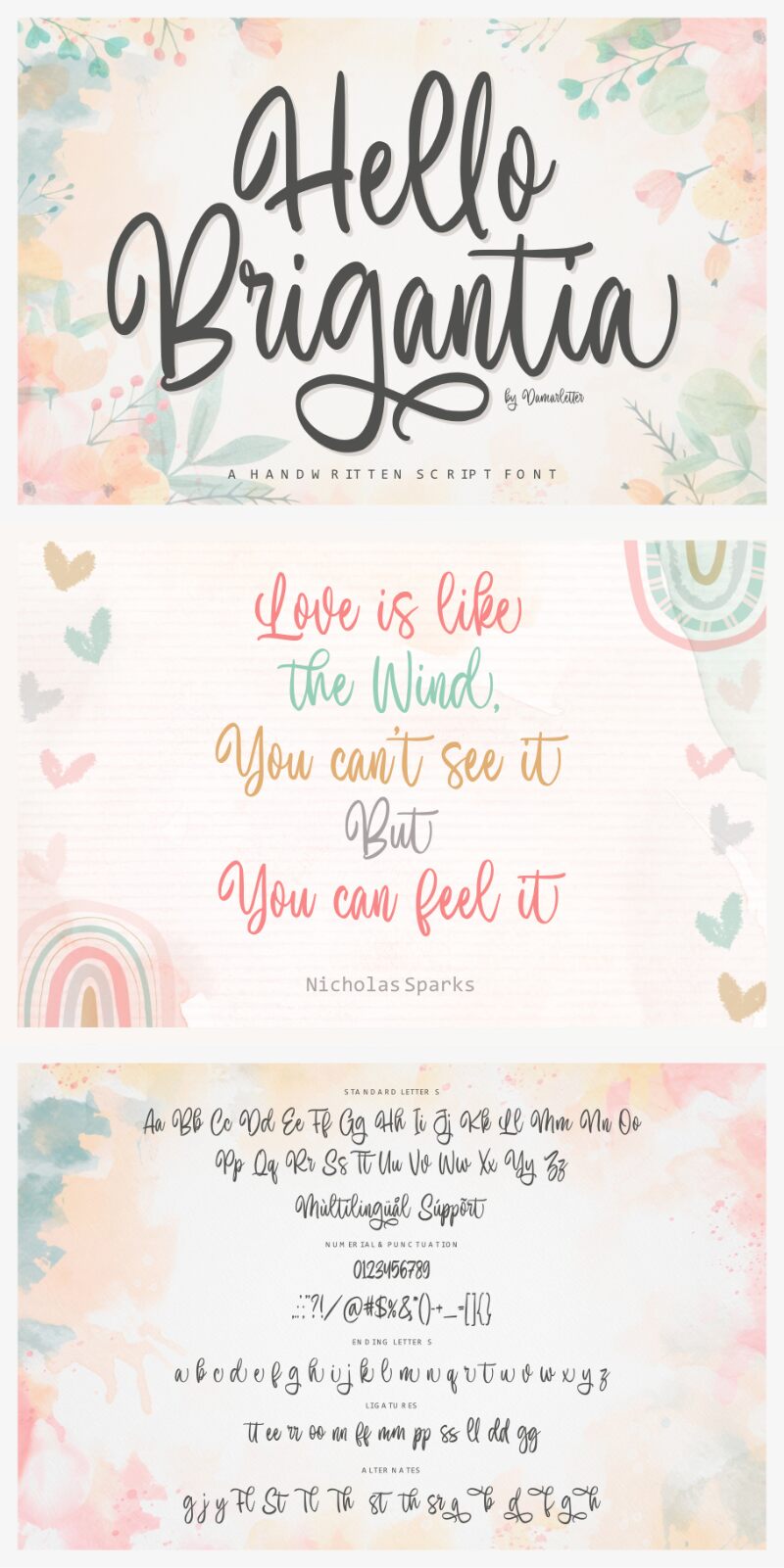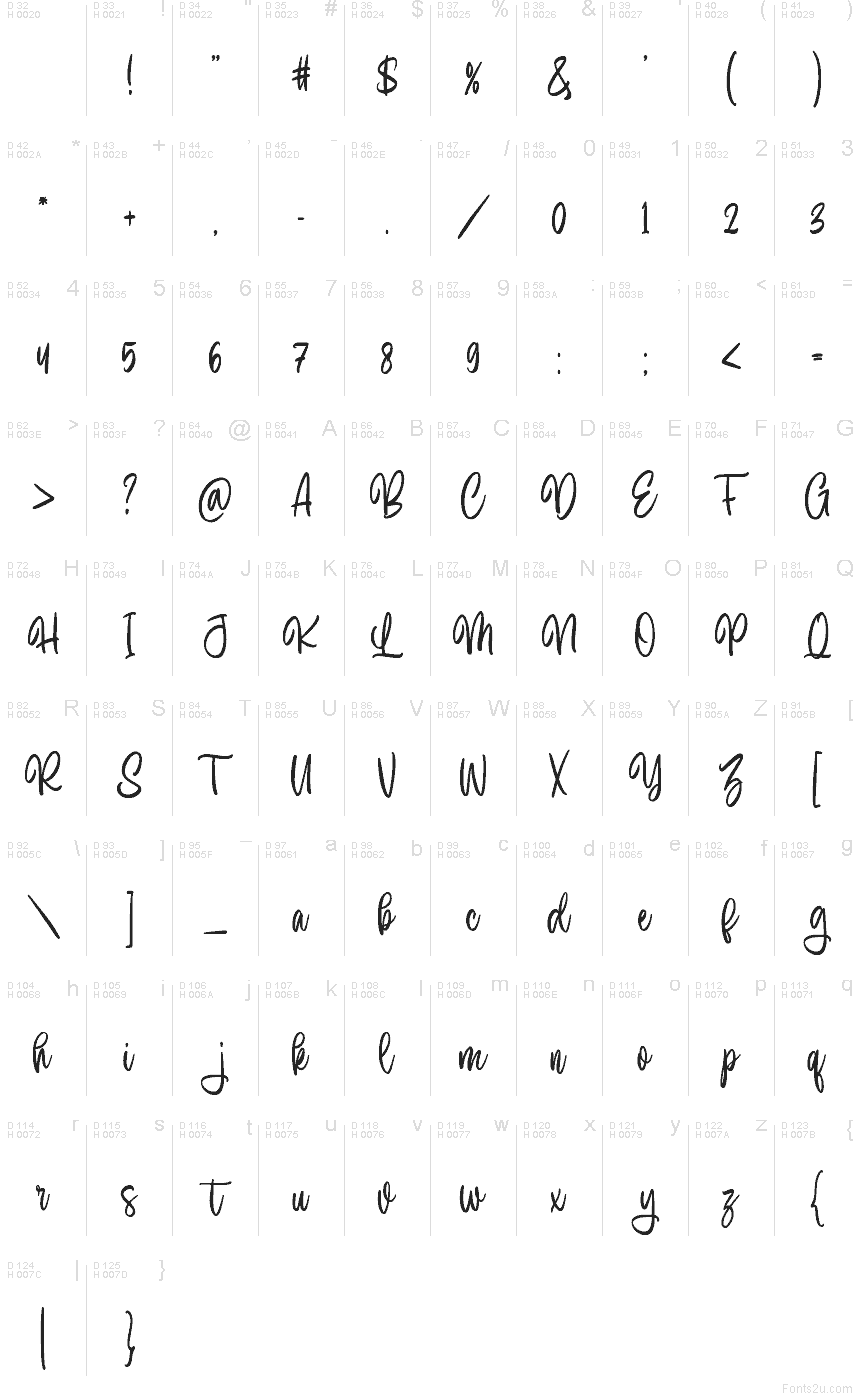
Hello Brigantia
Hello Brigantia, créée par Damarletter, est une police manuscrite gratuite au style cursif fluide, dotée d'un rythme naturel et décontracté. Ses traits liés s'enchaînent harmonieusement, tandis que ses boucles allongées, ses courbes arrondies et sa ligne de base dynamique lui confèrent une touche authentique et personnelle.
Hello Brigantia est parfaite pour les logos, les faire-part de mariage, les visuels de citations, les réseaux sociaux et le packaging nécessitant un aspect manuscrit. Cette police gratuite convient également aux signatures et aux cartes de vœux, car ses formes liées assurent un rendu expressif tout en restant très lisible.